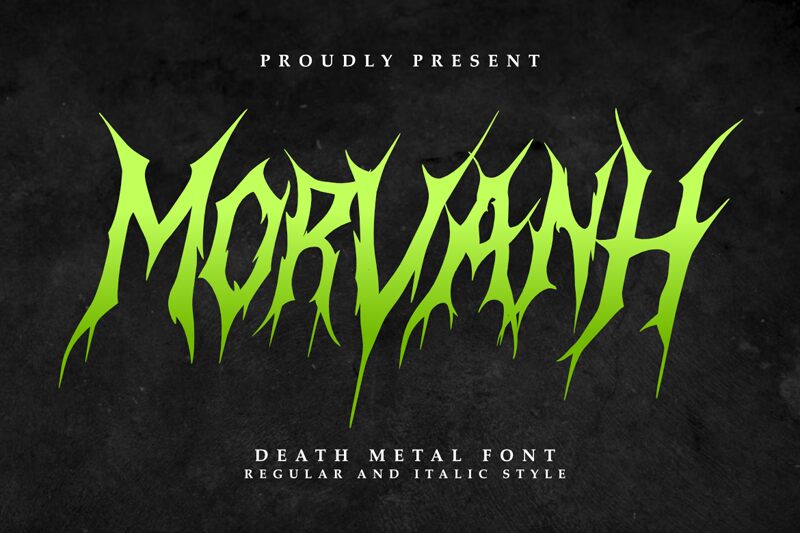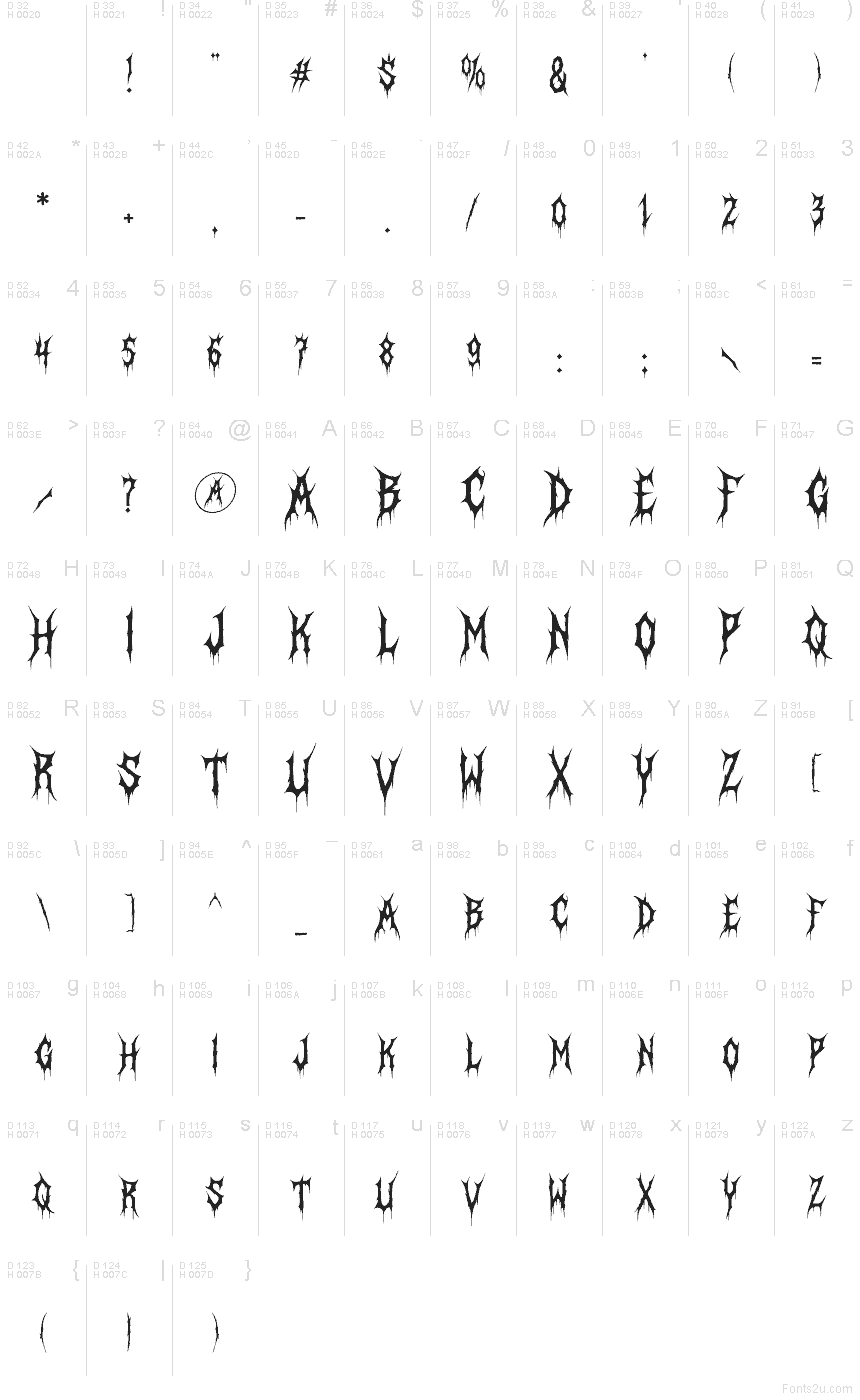
Morvanh Regular
La police Morvanh du Masyafi Studio est une police de caractères gothique gratuite de type display, dotée de traits acérés et déchirés ainsi que de bords pointus, donnant à chaque lettre un aspect sculpté plutôt que dessiné. Les formes s'élèvent en pointes fines et irrégulières, avec des espacements intérieurs disparates et un rythme brut et tortueux qui confère au logotype un caractère sombre et rituel.
Morvanh excelle pour les titres d'horreur, les visuels de groupes de metal, les flyers d'Halloween, les affiches de jeux et les logos nécessitant une esthétique dure et dramatique. Cette police gratuite convient également aux accents sur les affiches, aux couvertures d'albums et aux graphismes d'événements, car ses formes fracturées captent l'attention tout en conservant une personnalité forte et thématique.